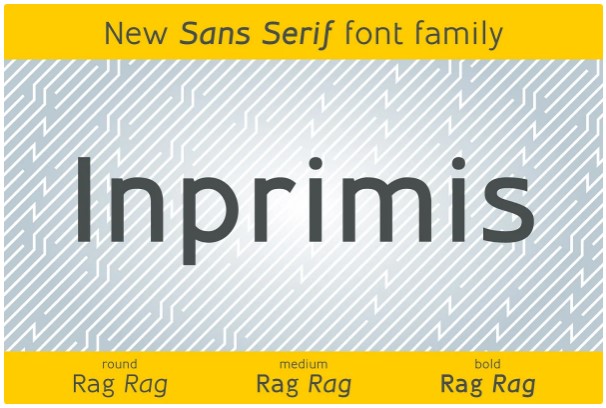
[Creativemarket] Inprimis Font (2021)
Inprimis - это новое семейство шрифтов sans serif, основанное на типографике "старого стиля", переведенной в эпоху moder. Смесь геометрических форм, старинной вязи и забытых (или забытых?) глифов.
Выпускается в 6 стилях: 3 вертикальных и 3 курсивных.
Каждый стиль включает расширенную языковую поддержку, лигатуры и многое другое.
¶ 490 глифов в каждом варианте (всего 2940)
¶ Стандартный + произвольная лигатура
¶ Альтернативный набор стилей
¶ Малая прописная
¶ Латинский расширенный
¶ Подстрочный + старый стиль фигурный линейный или табличный
¶ Числитель + Знаменатель + Подстрочный индекс + Надстрочный индекс
Сейчас семейство Inprimis находится в версии 1.26 и дополнено этими вариантами:
55 Обычный
56 Курсив
65 Средний
66 Средний курсив
75 Жирный
76 Полужирный курсив
Работа продолжается:
45 светлый
46 светлый курсив
85 чёрный
86 черный курсив
Inprimis невероятно полезен в большинстве творческих областей, таких как журнал, плакат, книга, композиция.